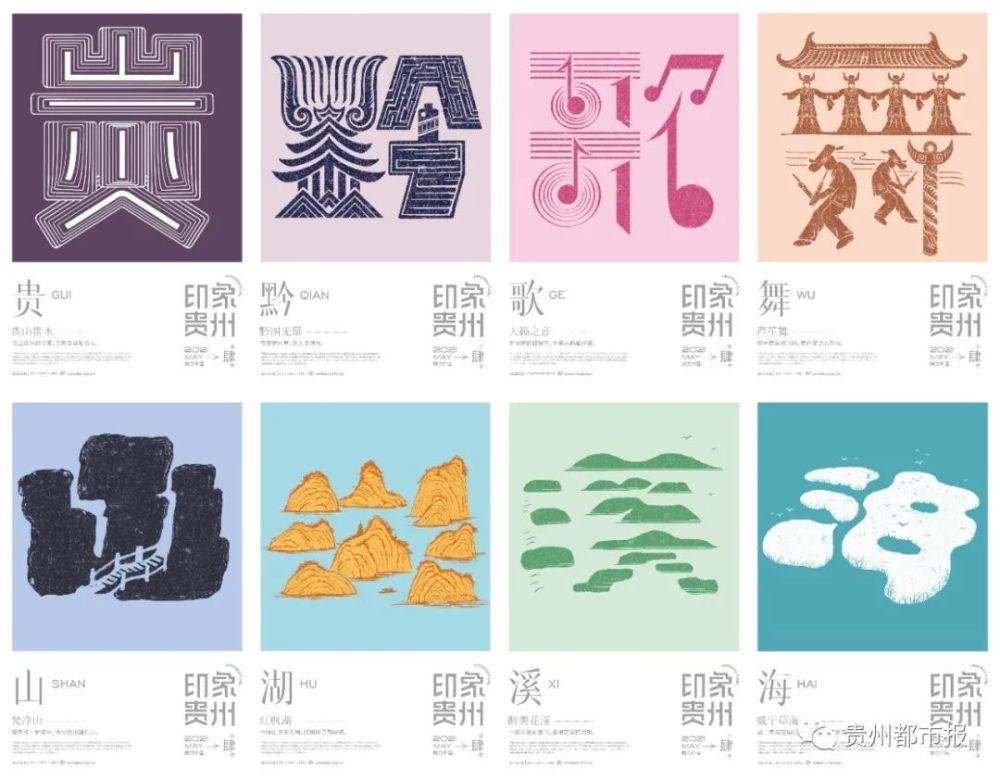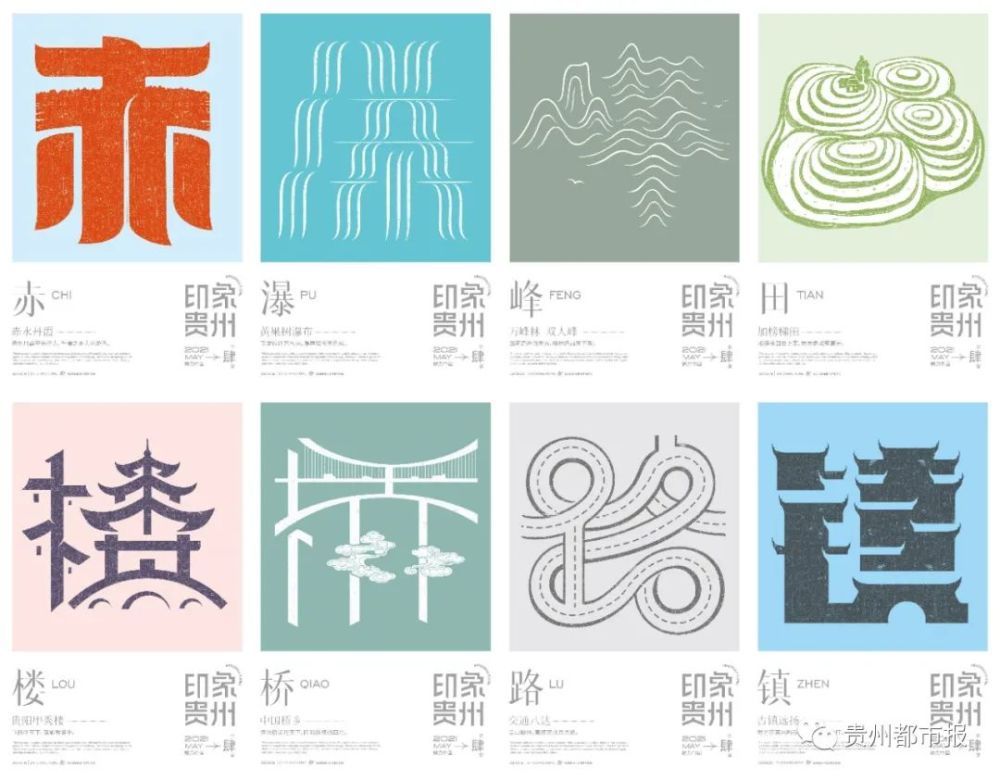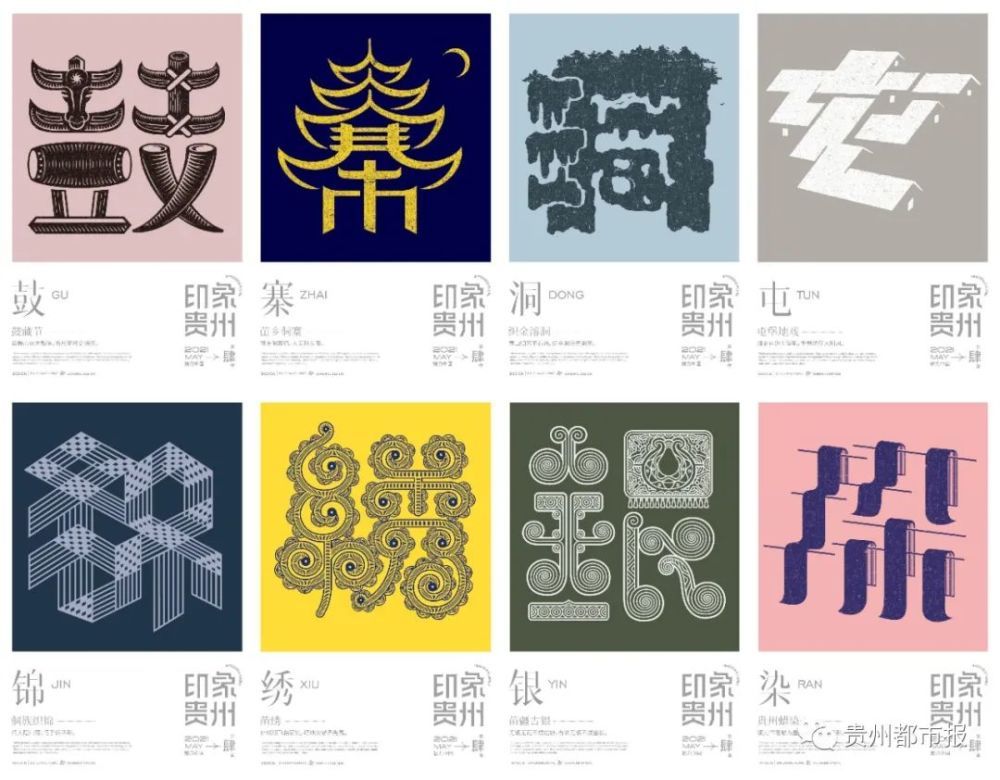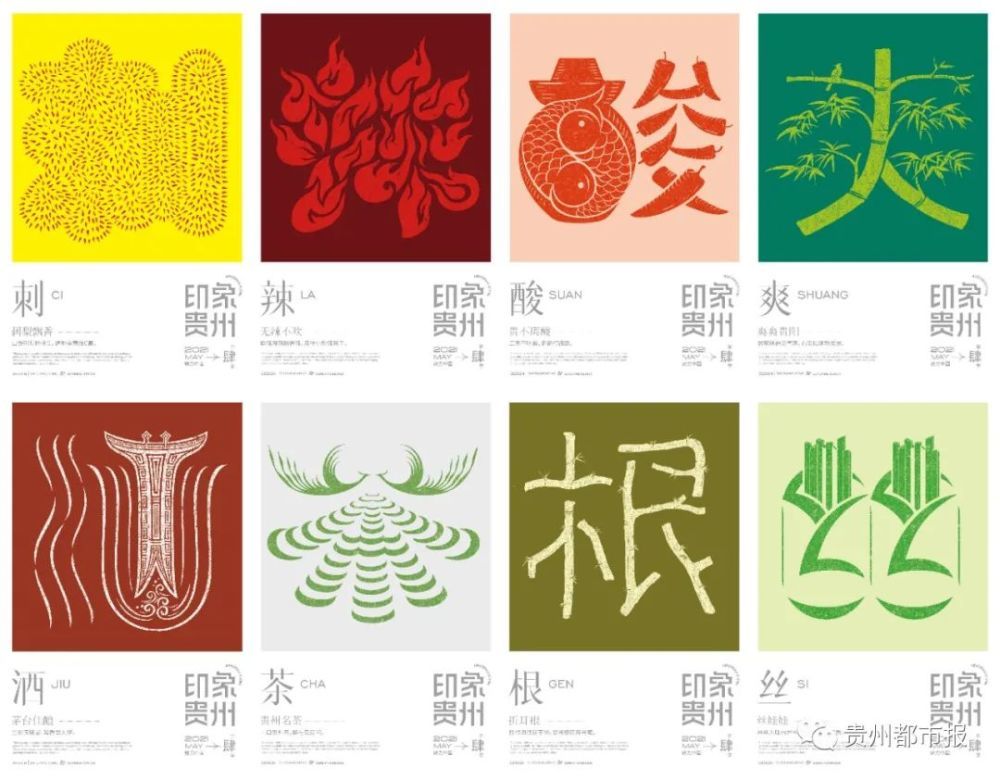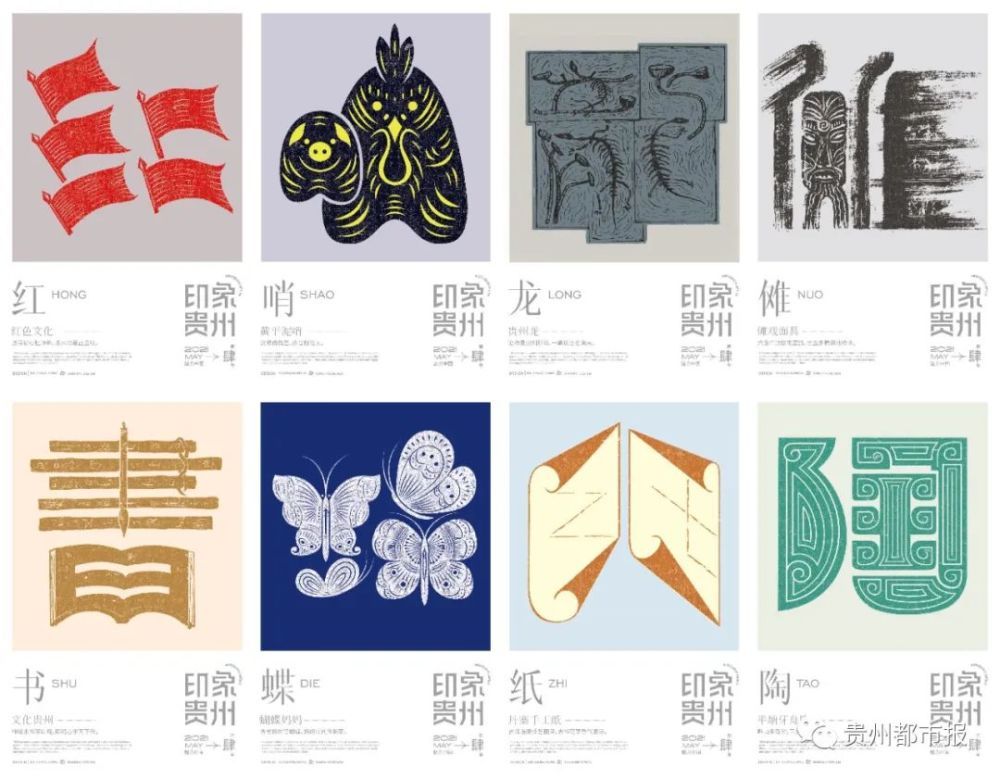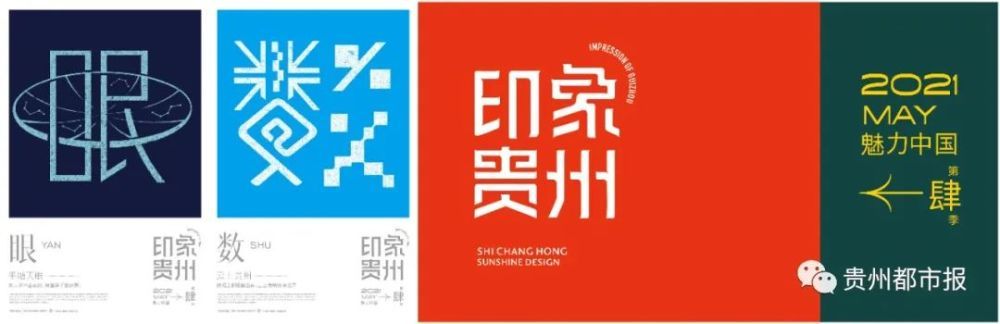
惊艳!42个字体创意带你重新认识贵州
每个人对于贵州的想法都是不一样的!
而贵州本土设计师石昌鸿用了近3年时间精心设计了42个字体创意,让人重新认识贵州、了解贵州,向世界传递贵州的美。
4月27日上午10点,《魅力中国》字体设计第四季“印象贵州”设计作品成果分享会上,石昌鸿设计的42个“印象贵州”字体创意新鲜出炉。
石昌鸿给大家介绍了这42个字体设计的创意与内涵:
▋“酸:贵不离酸,三天不吃酸,走路打蹿蹿。设计中将鱼、坛子、辣椒结合,酸的味道就体现出来了。”
▋“染:铜刀作笔蜡为墨,妙笔生花染黔彩。抽象的晾布场景,体现出贵州蜡染的记忆。”
▋“屯:烽烟远逝屯堡韵,千载犹存大明风。采风时看到当地用石屯盖房,不用瓦,体现出当地的地质特色。”
……
本次设计以贵州民俗风情、知名景点、自然风光等为源点进行创作,延续“魅力中国”系列作品,用创意传情,一字一景,用设计语言向外界传递大美贵州。
据了解,石昌鸿出生在贵州黎平阡洞侗寨,是一名擅于将现代文明与传统文化相结合的设计师,对贵州的山水有着极深的感情。“这些年贵州旅游蓬勃发展,越来越多外地朋友来到贵州旅游,我非常开心。我也为贵州的青山绿水骄傲着,贵州的惊世之美逐渐展现在世人面前,美丽的苗乡侗寨、迤逦的奇山秀水、多姿多彩的民族风情……都让世人惊艳不已!”这也更加激发了他的创作灵感。
石昌鸿说,作为一名贵州的设计师,他更想用设计语言去表达对这片土地的热爱。“用我自己的设计方式向世界表达贵州的美,期望越来越多的外地游客向往多彩贵州、爱上多彩贵州!”
石昌鸿主创设计的这42个字体创意,涉及贵州人文、气候、地形、特产、历史、现代科技等,他用这些字体创意,重新诠释贵州,用设计解构贵州文化和内涵,用文化创意的力量传播贵州好声音。
让我们跟随这一个个字体创意重新认识和了解多彩贵州——